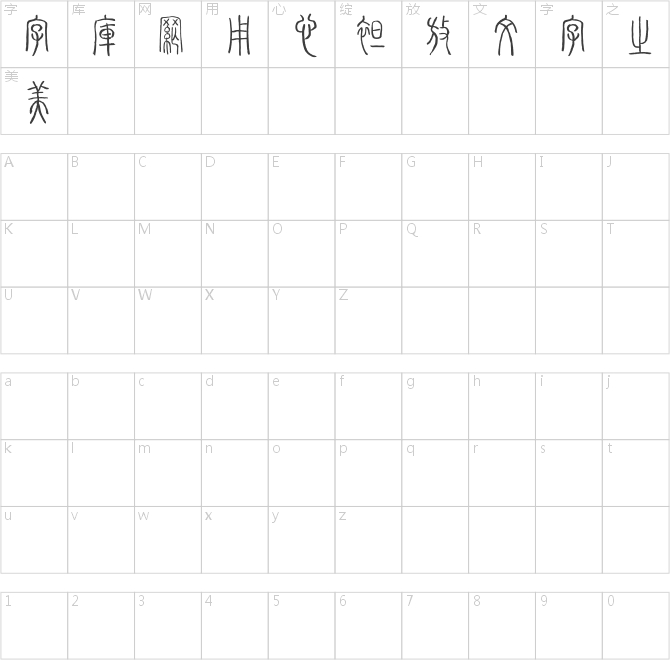
李親湖
李親湖 ,廣東省榮譽市民,中國文學藝術界聯合會名譽主席,廣東省文學藝術界聯合會終身名譽主席,廣東省政協書畫藝術交流促進會會員,法蘭西皇家美術學院皇家首席藝術家,加拿大阿爾伯塔大學榮譽博士學位,南粵文化之星,共和國杰出功勛文化藝家,中國文藝復興百杰人物。
李親湖篆體字庫的字長方偏瘦形,每一字端正,中鋒用筆,筆畫橫平豎直,圓勁均勻,粗細一致,畫與畫、豎與豎之問等距平行,隨意起隨意收,方中寓圓結字左右對稱,上下對稱,圓弧形筆畫左右傾斜度的對稱,上緊下松,美態多姿,仔細品嘗味道濃濃。視覺效果強烈地沖擊著眼球,讓品嘗者神游其間、沉醉于中。